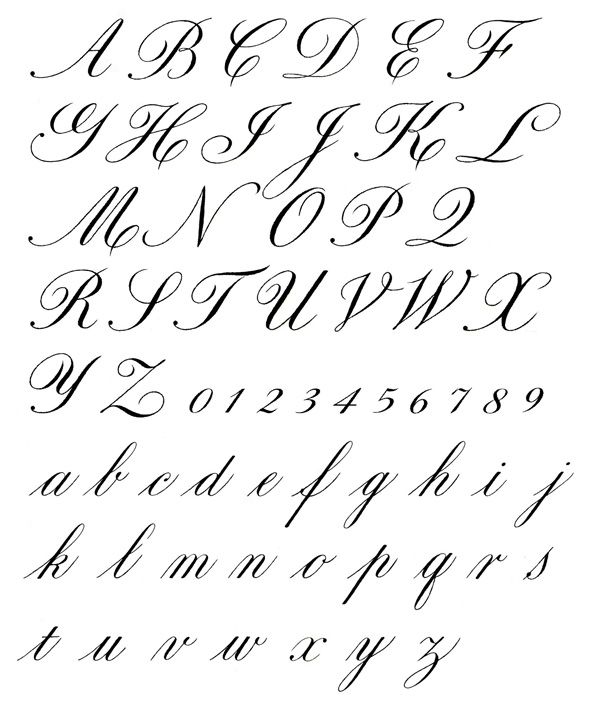
46 рукописных шрифтов, которые украсят любой проект
Перед вами список лучших бесплатных рукописных шрифтов со всего Интернета. Мы отобрали эффектные шрифты, которые отлично впишутся в один из ваших будущих проектов.
Шрифты не всегда должны быть дорогими. На самом деле, трудно поверить, что все опции из этой подборки можно скачать абсолютно бесплатно. Мы собрали лучшие рукописные шрифты со всего Интернета.
1. Buffalo
Этот красивый рукописный шрифт включает как прописные, так и строчные буквы, цифры и знаки препинания. Он идеально подойдет для множества проектов: от заголовков сайтов до поздравительных открыток, футболок и т.д.
2. The Historia
Historia — винтажный рукописный шрифт.
Все буквы будто нарисованы кистью. Этот вариант будет отлично смотреться на постерах, обложках книг и баннерах. Он состоит из прописных и строчных букв, цифр и альтернативных глифов.
3. Watch
Watch — современный рукописный шрифт в стиле граффити. Вы можете использовать его в дизайне веб-сайтов, постеров, для оформления постов в социальных сетях и многого другого. Он прекрасно впишется в дизайн, если проект связан с модой или его целевая аудитория преимущественно состоит из миллениалов.
4. Sophia Script
Этот элегантный шрифт — идеальный выбор, если вы разрабатываете дизайн поздравительных открыток или свадебных приглашений. Он выглядит уникально за счет растительных плавных линий. Шрифт включает 370 глифов и 115 альтернативных символов.
5. Stay High
Stay High — уникальный рукописный шрифт, который вызывает ассоциации с поп-культурой. Это отличный выбор для постеров, флаеров, баннеров и других цифровых или печатных проектов. Шрифт включает 200 лигатур и глифов.
Бесплатные рукописные шрифты
6. Coastline
Этот бесплатный рукописный шрифт может похвастаться впечатляющей текстурой и способен сделать любой дизайн аутентичным. Особенно удачно он будет смотреться на поздравительных открытках и приглашениях. Шрифт можно использовать бесплатно для личных проектов.
7. Adventurist
Этот массивный нарисованный кистью шрифт выглядит очень необычно. С его помощью вы создадите уникальные заголовки для постеров или флаеров. Скачайте Adventurist бесплатно для личных проектов.
8. Richmond
Еще один креативный рукописный шрифт с интересной текстурой. Благодаря минималистичному дизайну он идеально подойдет для различных цифровых проектов и полиграфии. И что самое приятное — его можно использовать абсолютно бесплатно как в личных, так и в коммерческих проектах.
9. GoodHood
Если вы ищете шрифт в классическом ретро-стиле, этот вариант — именно то, что вам нужно. Игривые буквы мгновенно вызывают ассоциации с 90-ми.
10. Albertiny
Этот винтажный рукописный шрифт будет эффектно смотреться на этикетках продуктов и вывесках. Он включает как прописные, так и строчные буквы. Используйте его бесплатно в личных проектах.
11. Monique Script
Monique Script — элегантный рукописный шрифт с минималистичным дизайном. Он идеально подходит для всевозможных поздравительных открыток, визитных карточек, свадебных приглашений. Шрифт можно использовать бесплатно в коммерческих проектах.
12. Southam
Если вы искали стильный рукописный шрифт для визитной карточки, этот вариант именно для вас. Изысканный дизайн смотрится профессионально. Вы можете использовать его бесплатно в личных целях.
13. Calista
Calista — трендовый рукописный шрифт, который пригодится вам для оформления постов в социальных сетях и других креативных проектов. Кроме того, он будет прекрасно выглядеть на футболках. Шрифт бесплатен для личных проектов.
14. Jelantik
Если вам нужен минималистичный рукописный шрифт, эта опция стоит внимания. Элегантные буквы будут отлично смотреться в различных цифровых и печатных проектах. Используйте его бесплатно в личных целях.
15. Blankeny
Этот бесплатный рукописный шрифт идеально подходит для разных творческих проектов, например, школьных баннеров, постеров и даже логотипов. Вы можете скачать его и использовать в личных целях бесплатно.
16. Crawley
Crawley — красивый рукописный шрифт в стиле ретро. Он просто создан для логотипов, постеров и заголовков сайтов. Скачайте бесплатно демо-версию шрифта и используйте ее в личных проектах.
17. TAHU!
Этот минималистичный рукописный шрифт выглядит современно и способен мгновенно привлечь внимание. Он состоит из прописных и строчных букв, цифр, знаков препинания и поддерживает несколько языков. Используйте его совершенно бесплатно как в личных, так и в коммерческих проектах.
18. Hamster Script
Дизайн этого креативного рукописного шрифта вдохновлен леттерингом и вывесками.